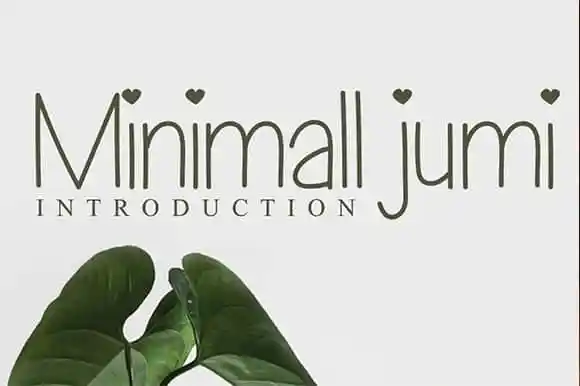
Minimall Jumi Font – Download Grátis
A fonte Minimall Jumi é perfeita para qualquer projeto que busca uma aparição elegante e sofisticada. Conhecida por sua tipografia serif, esta fonte se destaca como uma opção versátil para diferentes usos gráficos. Seja ela uma impressão em cartão de convite de casamento ou um post em redes sociais com design minimalista, a Minimall Jumi irá dar ao seu projeto aquela nota especial que torna-o único e chamativo. Ideal para uso em embalagens de produtos, cartões de visita, materiais promocionais e até mesmo marcas de fotografia, esta fonte é perfeita para quem busca uma aparição elegante sem comprometer o cuidado com detalhes. Seu charme sofisticado faz dela uma escolha ótima para criar um design que se destaque em qualquer projeto, mantendo sempre a graça e requinte tradicionais das fontes serif. Com Minimall Jumi na sua paleta de recursos gráficos, você pode criar designs que ressoam com sofisticação sem perder o brilho da arte do desenho manual. Seja em grandes dimensões para exposições ou em pequenos detalhes para aplicativos digitais, a Minimall Jumi oferece um toque de elegância e charme. Quebre as regras e faça seus projetos se destacarem com uma fonte que combina elegância e sofisticação perfeitamente.